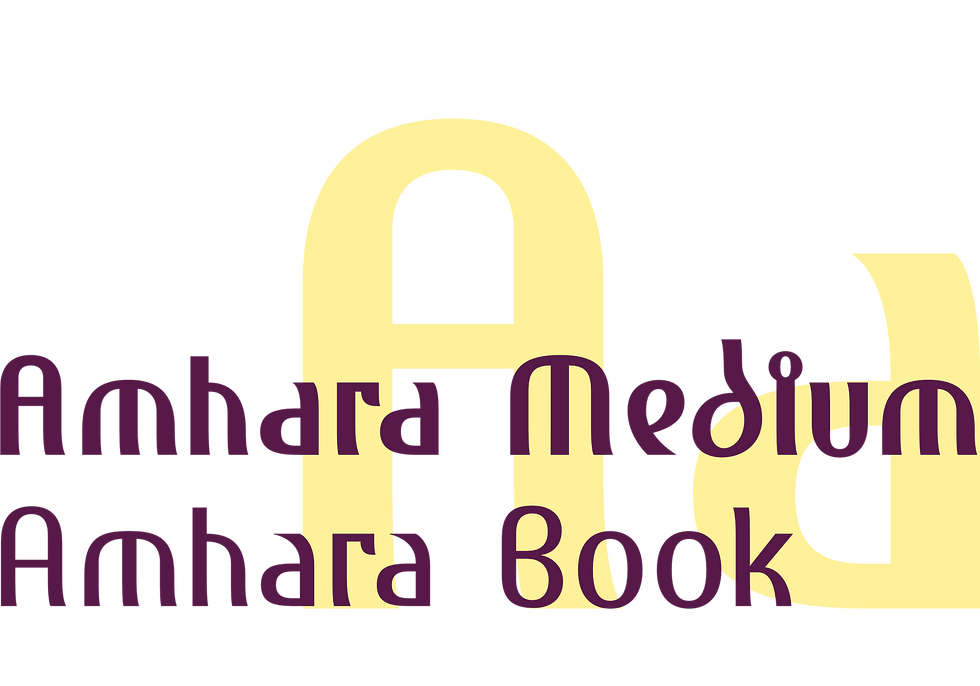
Une expérience typographique : un alphabet « latin » inspiré de l'écriture éthiopienne Ge'ez.
- décoratif
- exotique
- étrange
- ni antiqua ni sans serif
Kush, Punt, Saba, Aksum, Abbesinien, Éthiopie – les noms de ce pays d'Afrique de l'Est ont changé au cours de son histoire millénaire. Peu d'États ont une histoire et une tradition culturelle aussi longues. Indépendante depuis des temps immémoriaux, l'Éthiopie a longtemps été considérée comme l'un des « grands » empires. Elle est également considérée comme le plus ancien pays chrétien.
La langue amharique d'Éthiopie et l'écriture correspondante « Ge'ez » se sont développées à partir d'origines sémitiques dans le sud de l'Arabie.
« Ge'ez » est la seule écriture d'origine sémitique qui s'écrit de gauche à droite.
En raison d'une tradition chrétienne qui s'étend désormais sur plus de 1600 ans et d'une relation très étroite avec le bassin méditerranéen hellénistique à la fin de l'Antiquité, on peut également reconnaître des emprunts au grec dans l'écriture amharique.
L'écriture amharique est traditionnellement écrite avec une large pointe de plume. C'est pourquoi elle a le ductus typique qui caractérise également les écritures onciales de la fin de l'Antiquité et du début du Moyen Âge.
Et comme la « Ge'ez » a servi de modèle à l'« Amhara » d'ingoFonts, ces caractéristiques se retrouvent également dans l'« Amhara ».
Les larges verticales, particulièrement accentuées par la tenue horizontale de la plume, sont typiques de l'écriture éthiopienne.
La forme la plus fréquente et donc la plus marquante pour l'impression générale est l'arc ouvert en bas.
L'arrondi symétrique à la transition entre le tracé large et le tracé fin, puis à nouveau le tracé large, détermine très largement l'aspect de l'écriture.
Les nombreuses formes de tirets, de crochets, de cercles et d'appendices de toutes sortes sont typiques des écritures sémitiques. Il en résulte une richesse de formes dans les détails qui permet de composer les éléments des lettres européennes.
Tout cela donne à la police de caractères « Amhara » un aspect quelque peu sacré. Du moins, malgré l'étrangeté des formes dans le détail, elle semble étrangement familière dans son ensemble.
L'« Amhara » est né de la transposition des formes typiquement amhariques dans l'alphabet d'Europe occidentale. Presque toutes les caractéristiques formelles du « Ge'ez » ont pu être reprises pour les lettres minuscules ; certains caractères – B C H J M O T W Y Z d e g m n p t u y 2 4 8 – ont même pu être repris intégralement (avec une signification différente bien sûr).
Les signes amhariques ont pour la plupart un tracé initial suggéré depuis le haut à gauche et un petit tracé vers le bas à droite. L' » Amhara » tente de conserver cette direction de mouvement.
Les minuscules donnent une impression d'agitation et ne permettent pas une lecture fluide. On garde ainsi une impression d'étrangeté et d'exotisme du modèle africain.
L' » Amhara Book », plus léger, est une variante un peu moins épurée et donc plus lisible. Ses formes et ses proportions se rapprochent prudemment de celles des caractères occidentaux.
Pour les lettres f g h p t y z, des formes de caractères alternatives sont également disponibles.
Au sens strict, les majuscules constituent un alphabet à part entière. Contrairement à nos majuscules romaines classiques, les caractères amhariques renoncent presque entièrement aux formes triangulaires pointues. Il a donc fallu trouver d'autres solutions formelles pour les formes en fait angulaires et obliques des lettres latines A E F K M N R V W X Y. Il existe certes en « Ge'ez » des signes dentelés en forme d'éclair, mais seule la forme Z est transposable.
Les majuscules d'« Amhara » ont ainsi un aspect très agréable et rond. Un texte en majuscules dans cette police semble agréablement calme, car on retrouve toujours les mêmes quelques formes de base dans les divers caractères. C'est un cas rare où un texte en VERSALE semble presque doux au lieu d'être sévère.
L'« Amhara » contient une série de ligatures qui résolvent les combinaisons de lettres inesthétiques : fa ff fi fl ft gg gt ll st ta th ti tt tu tz ainsi que, activables séparément, les rares ligatures Th ch ck ffi ffl.